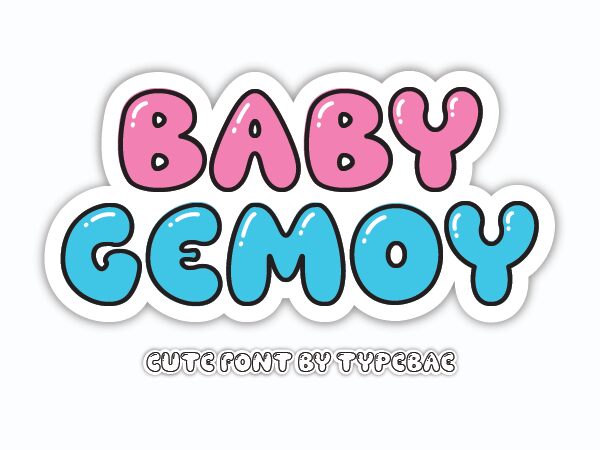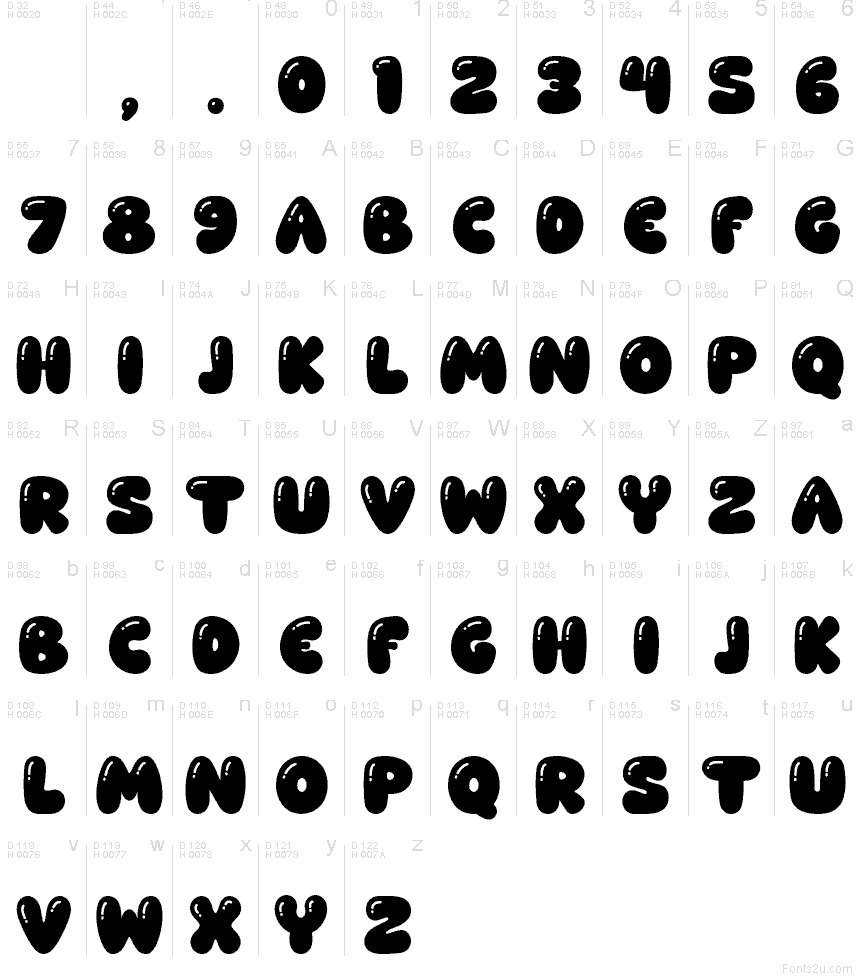
Baby Gemoy, creata da Iqbal Pauji, è un font cartoon gratuito che ricorda lettere di gomma da masticare gonfie, immerse nell'inchiostro lucido e arricchite da piccoli riflessi che le rendono vivaci e giocose. Le forme piene e arrotondate rimangono leggibili anche a colpo d'occhio, così il tuo messaggio arriva dritto al punto con simpatia.
Baby Gemoy è perfetto per inviti a feste per bambini, fogli di adesivi, packaging di giocattoli, anteprime YouTube, loghi divertenti, locandine scolastiche e copertine per post o reel. Impostalo leggermente più grande del solito per far respirare le sue curve morbide e abbinalo a un carattere sans serif pulito come Poppins o Montserrat per i testi di supporto: questo font gratuito pensa al divertimento, il sans serif pensa alle informazioni.